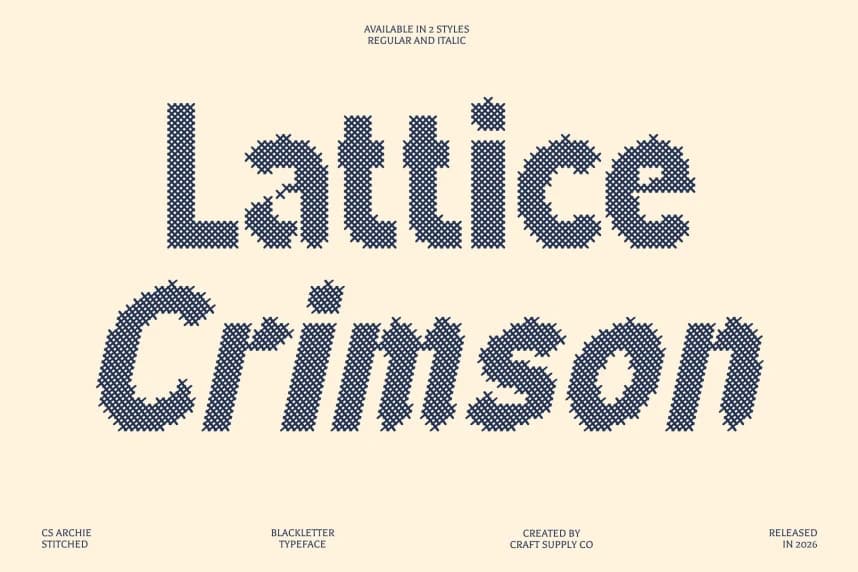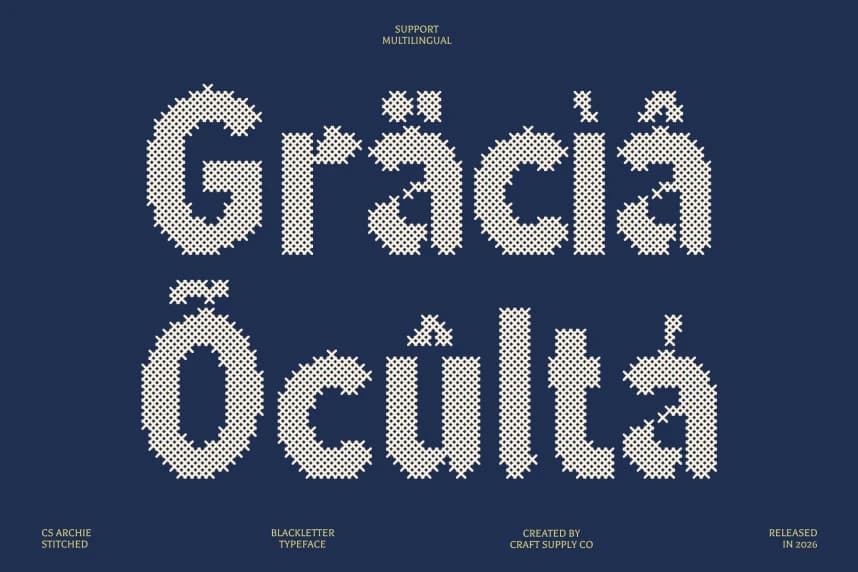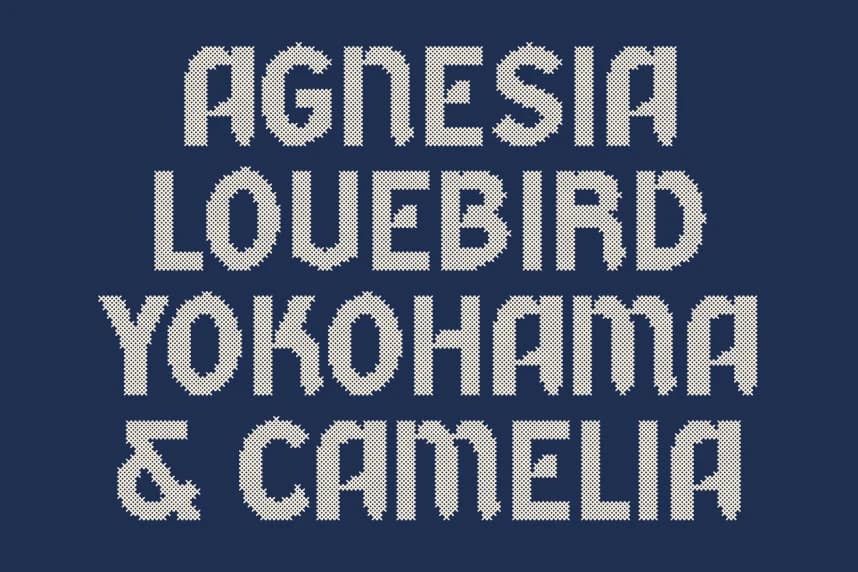
CS Archie Dikişli Yazı Tipi
CS Archie Stitched Font – Blackletter Font: Klasik Zarafet, Modern Cesurlukla Buluşuyor. El yapımı derinlikle klasik Blackletter. Bu, klasik zarafeti cesur çağdaş güçle harmanlayan modern bir Blackletter sergileme yazı tipidir.
CS Archie Stitched Font – Blackletter Font: Klasik Zarafet Modern Cesaretle Buluşuyor Klasik Blackletter, El Yapımı Derinlikle. Bu, klasik zarafeti cesur çağdaş güçle harmanlayan modern bir Blackletter gösterim yazı tipidir.